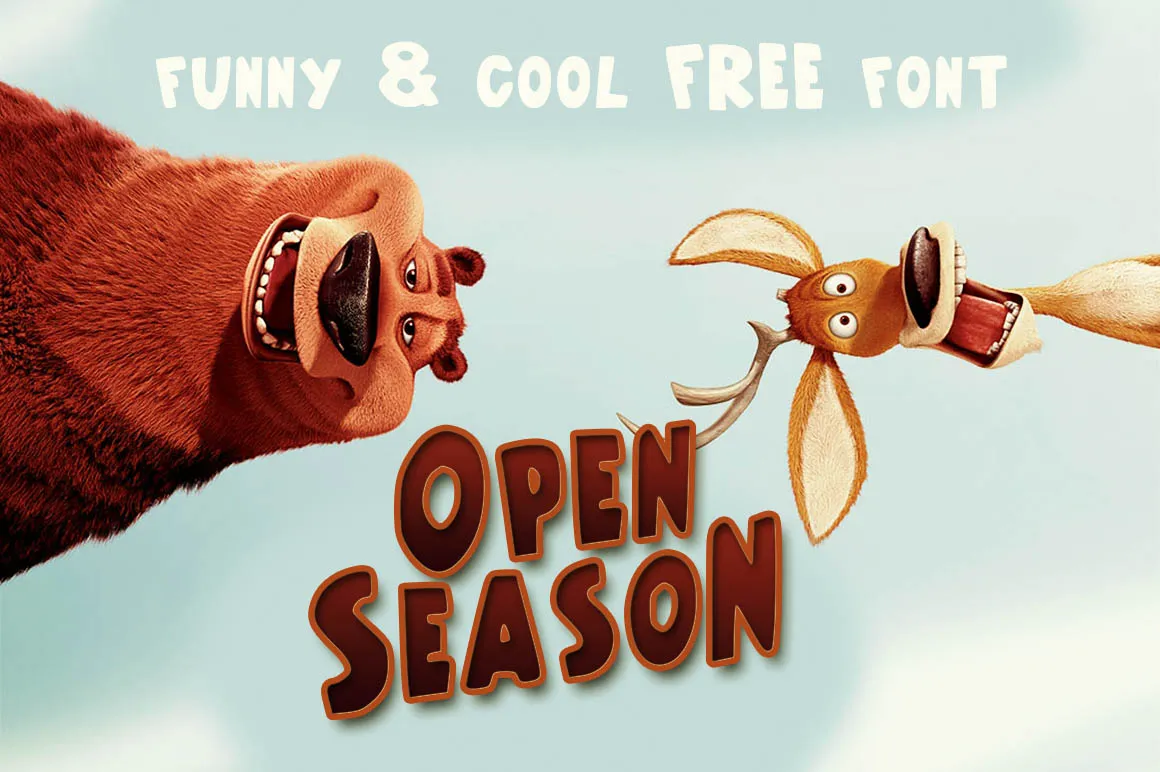
Open Season Font é uma escolha perfeita para quem procura um estilo criativo e divertido para projetos digitais. Inspirada na popular animação de filmes, esta fonte artesanal foi desenvolvida por João Pereira e traz um toque descontraído e original que não pode deixar ninguém indiferente. Com seu traçado de rua coeso e suas ideias brilhantes, Open Season é perfeito para uma variedade de propósitos. Suas linhas fortes e vibrantes fazem dela uma escolha excelente tanto para os desenhos animados infantis quanto para histórias em quadrinhos criativas. Este fonte está repleto de personalidade e permite que você personalize seu design, tornando-o único e atraente. Seja para criar um logo memorável ou para adicionar um toque diferente ao seu próximo projeto gráfico, Open Season é uma ótima escolha. O seu designer Hamilton trouxe-lhe vida com sua habilidade de artesanato em letras digitais, resultando num estilo único que se destaca em qualquer trabalho de design digital.